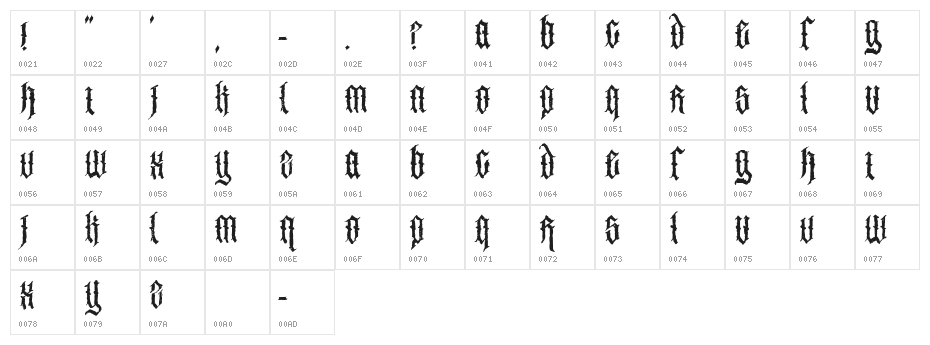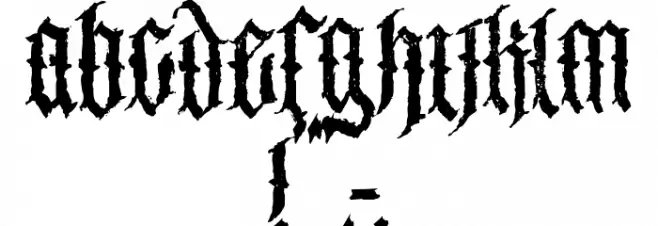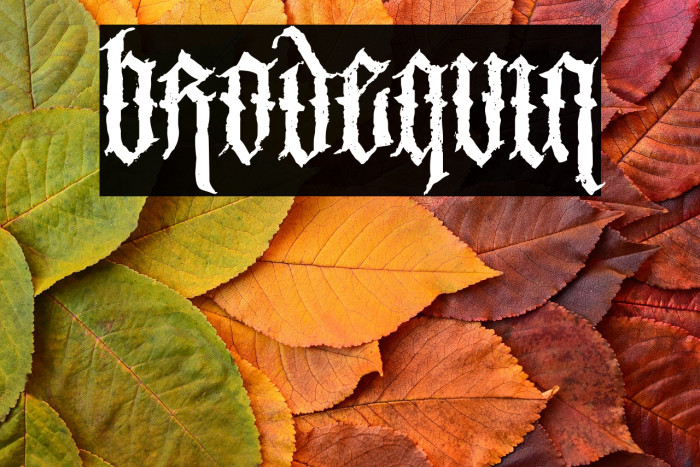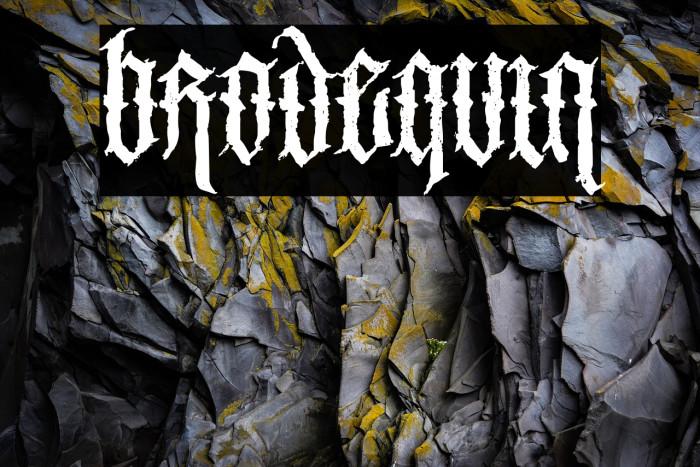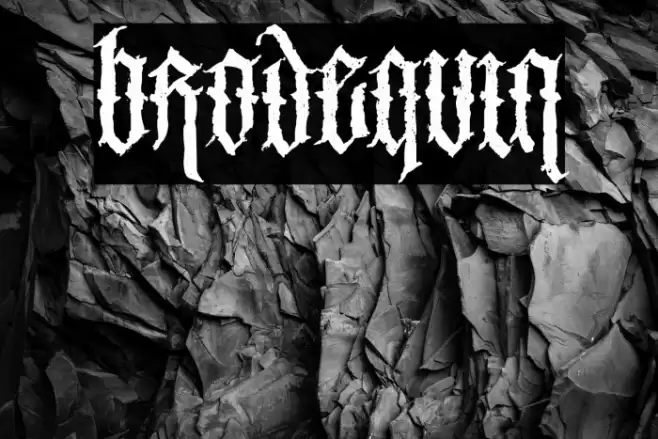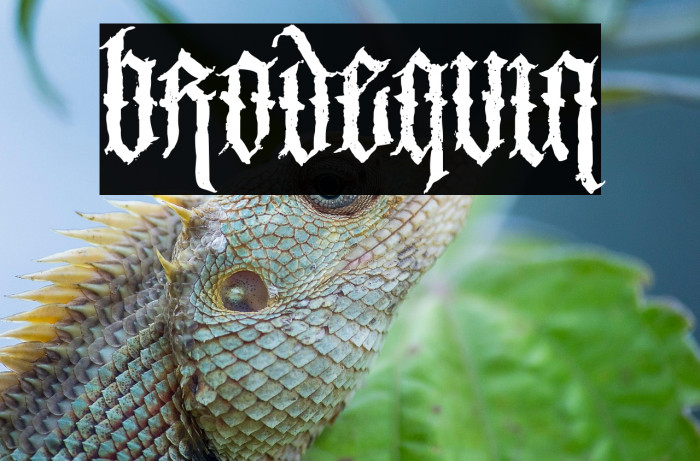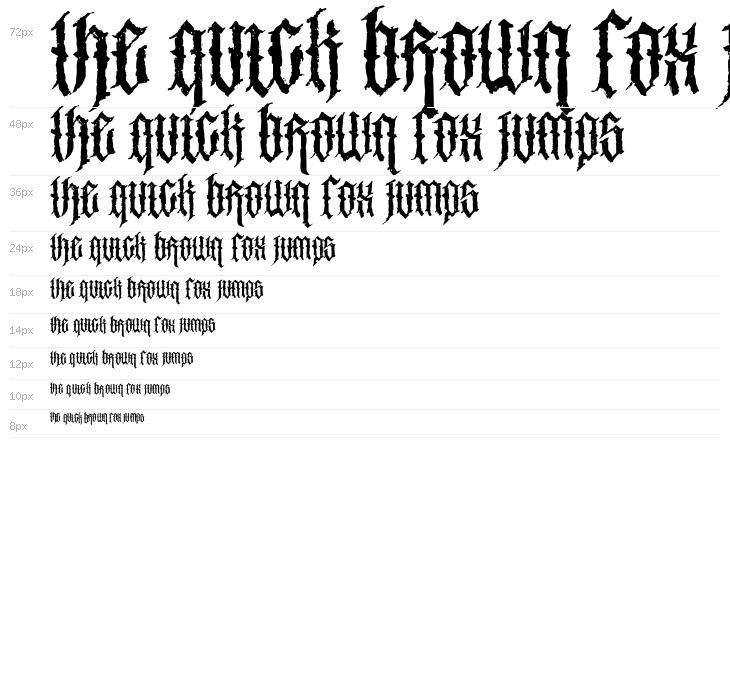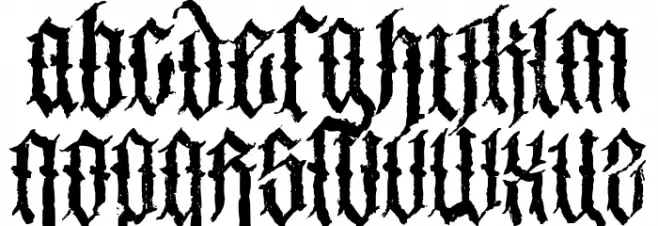
Brodequin Font
✎ Gothic
| Categorii | Gothic |
| Stil general | Gothic, Medieval |
| Proiecte propuse | Suitable for use in branding, posters, album covers, and any design requiring a historical or gothic theme. |